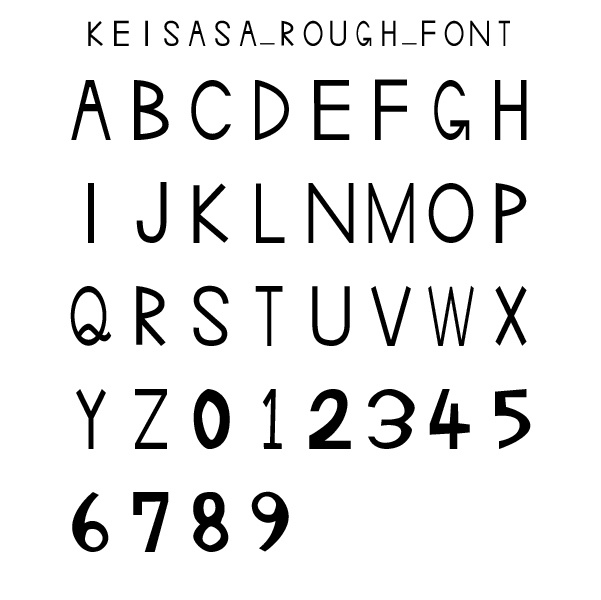
Keisasa Rough Font Keisasa Rough Fontは、手書きのラフな質感を活かしたフォントで、ナチュラルで親しみやすい印象を与えます。ラフな線の揺らぎが温かみを生み出し、印象的なタイトルやロゴ作成に最適です。あえて整えすぎない絶妙なバランスが、ユニークさと味わい深さを演出します。大文字と数字のみの構成です。 スペック フォント形式:TrueTypeフォント(.ttf) スタイル:ラフ、ナチュラル、手書き風 対応言語:英語(アルファベット・数字のみ) 使用可能なソフトウェア:Adobe Illustrator、Photoshop、InDesign、Microsoft Word、Google Docs など ライセンス:商用利用可能(個人・商業利用ともにOK) 特徴とこだわり Keisasa Rough Fontは、手書きのようなラフさと温かみのあるデザインが特徴です。フォーマルすぎない親しみやすさがあり、タイトルやロゴ、ポスター、ショップカードなど、デザインにアクセントを加えたいときに最適です。 不規則なラインと微妙なゆらぎによって、デジタルフォントにはない「人の手」を感じさせる温もりを演出します。ナチュラルな雰囲気を活かしたいデザインにぴったりなフォントです。 制作の道のり このフォントは、機械的すぎず、あたたかみのあるフォントを作りたいという思いから誕生しました。手書き風のラフなラインを意識し、繊細さと力強さを両立するバランスにこだわって設計。どこか懐かしく、親しみやすい雰囲気を目指し、細部まで丁寧に作り込みました。 ライセンスについて このフォントは、商業利用を含むさまざまな用途にご使用いただけます。ただし、再配布は禁止しております。著作権は放棄していませんので、利用の際は著作権を尊重してください。 Keisasa Rough Fontは、ナチュラルで親しみやすいデザインを実現するフォントです。ぜひ、あなたの次のデザインプロジェクトにお役立てください。 収録文字 A〜Z 0〜9 Keisasa Rough Font is a typeface that features a natural, hand-drawn rough texture, giving your designs a warm and approachable feel. Its slightly irregular strokes create a sense of authenticity, making it perfect for impactful titles and logo designs. With an intentionally unpolished balance, this font delivers uniqueness and character. It includes uppercase letters and numbers only. Specifications Font Format: TrueType Font (.ttf) Style: Rough, Natural, Hand-drawn Supported Languages: English (Alphabets & Numbers Only) Compatible Software: Adobe Illustrator, Photoshop, InDesign, Microsoft Word, Google Docs, and more License: Commercial use allowed (for both personal and commercial projects) Features & Highlights Keisasa Rough Font captures the charm of hand-drawn lines, giving your work a casual yet distinctive look. Its informal, friendly style makes it ideal for titles, logos, posters, shop cards, and any project where you want to add a personal touch. The irregular strokes and subtle wobble in the lines create a warmth that’s hard to achieve with standard digital fonts. This typeface is a perfect choice for designs aiming for a natural, handmade vibe. The Creative Journey This font was created with the goal of developing a typeface that feels less mechanical and more human. The hand-drawn roughness was carefully crafted to balance delicacy with boldness. Inspired by nostalgia and friendliness, each character was thoughtfully designed to give an inviting and authentic impression. License Information This font can be used for a wide range of applications, including commercial projects. Redistribution of the font itself is not permitted. Copyright is retained, so please respect the rights of the creator when using the font. Keisasa Rough Font is a warm and approachable typeface that adds a handcrafted touch to your designs. We hope it enhances your next creative project! This is an original TTF font designed by Japanese artist Keisasa. Available for commercial use. Ideal for creative design, games, and more.